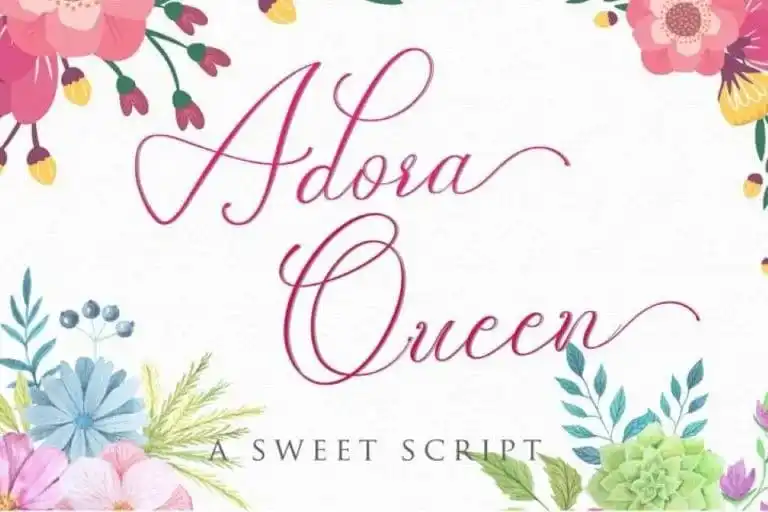
Adora Queen Calligraphy Font – Download Grátis
Adora Queen Calligraphy Font é uma elegante e sofisticada fonte de calligrafia script que traz a sensação natural de uma escrita a mão, ideal para criar design pessoalizado com um toque único e delicado. Esta fonte foi projetada pela Din Studio em um processo criativo meticuloso e agora está disponível para download no formato digital. Com suas ligações e alternativas sutis, Adora Queen Calligraphy Font oferece uma variedade de opções que podem ser utilizadas com facilidade para complementar qualquer projeto gráfico. Quando aplicada ao seu design, essa fonte vai conferir um toque natural e encantador a cada detalhe, tornando seus trabalhos ainda mais belos e sofisticados. Seja para criar cartões de aniversário, materiais educacionais ou simplesmente decorar suas páginas de diário, Adora Queen Calligraphy Font é perfeita para designers que desejam dar um toque elegante à sua arte. Adora Queen Calligraphy Font não apenas oferece uma variedade de ligações e alternativas para aprimorar o design, mas também proporciona um sentimento autêntico e criativo. Sua beleza natural faz dela uma escolha perfeita para designers em busca de fontes que se destacam entre as demais, oferecendo uma solução conveniente e impecável para quem procura trazer um toque especial a seus projetos.